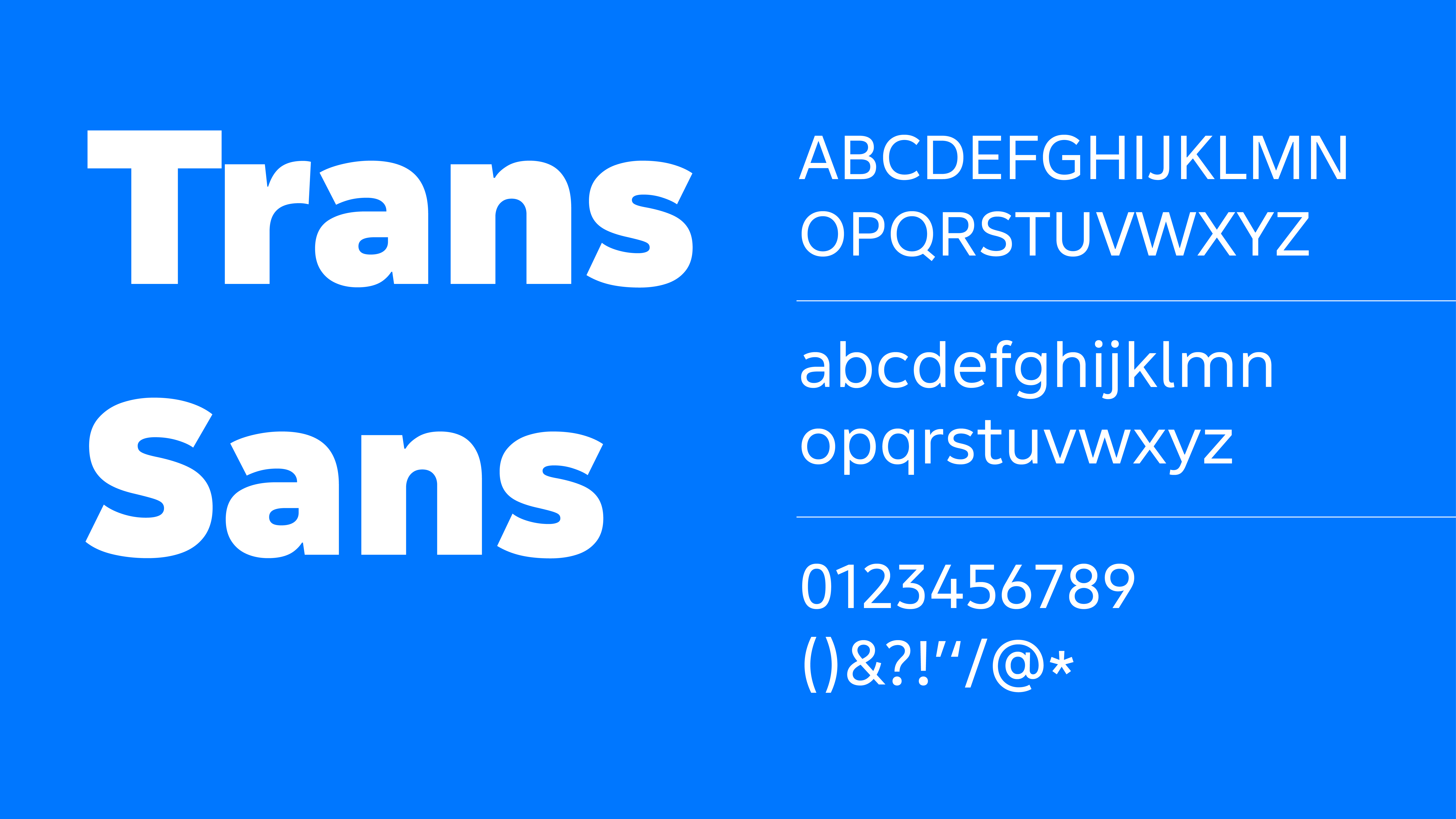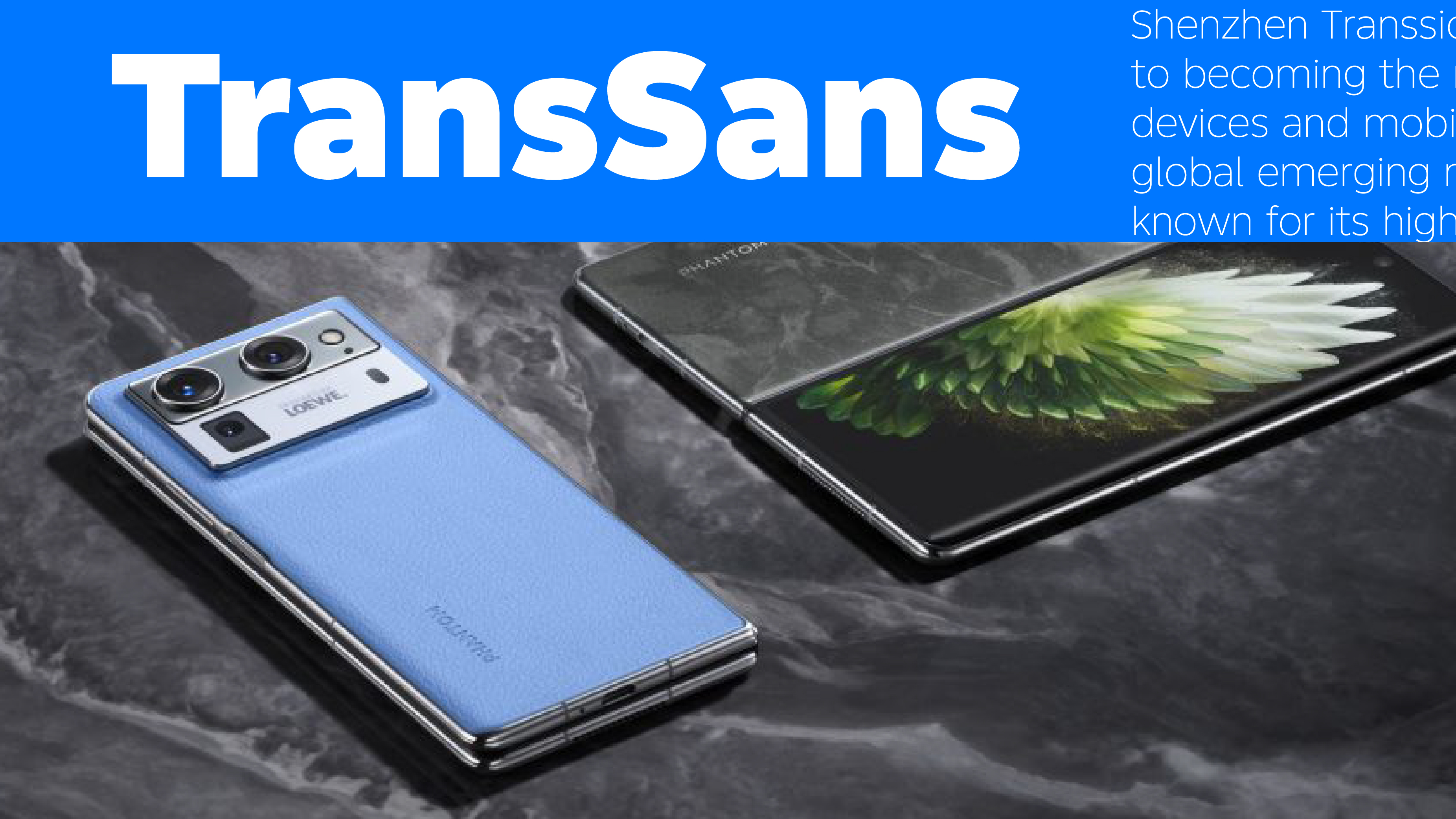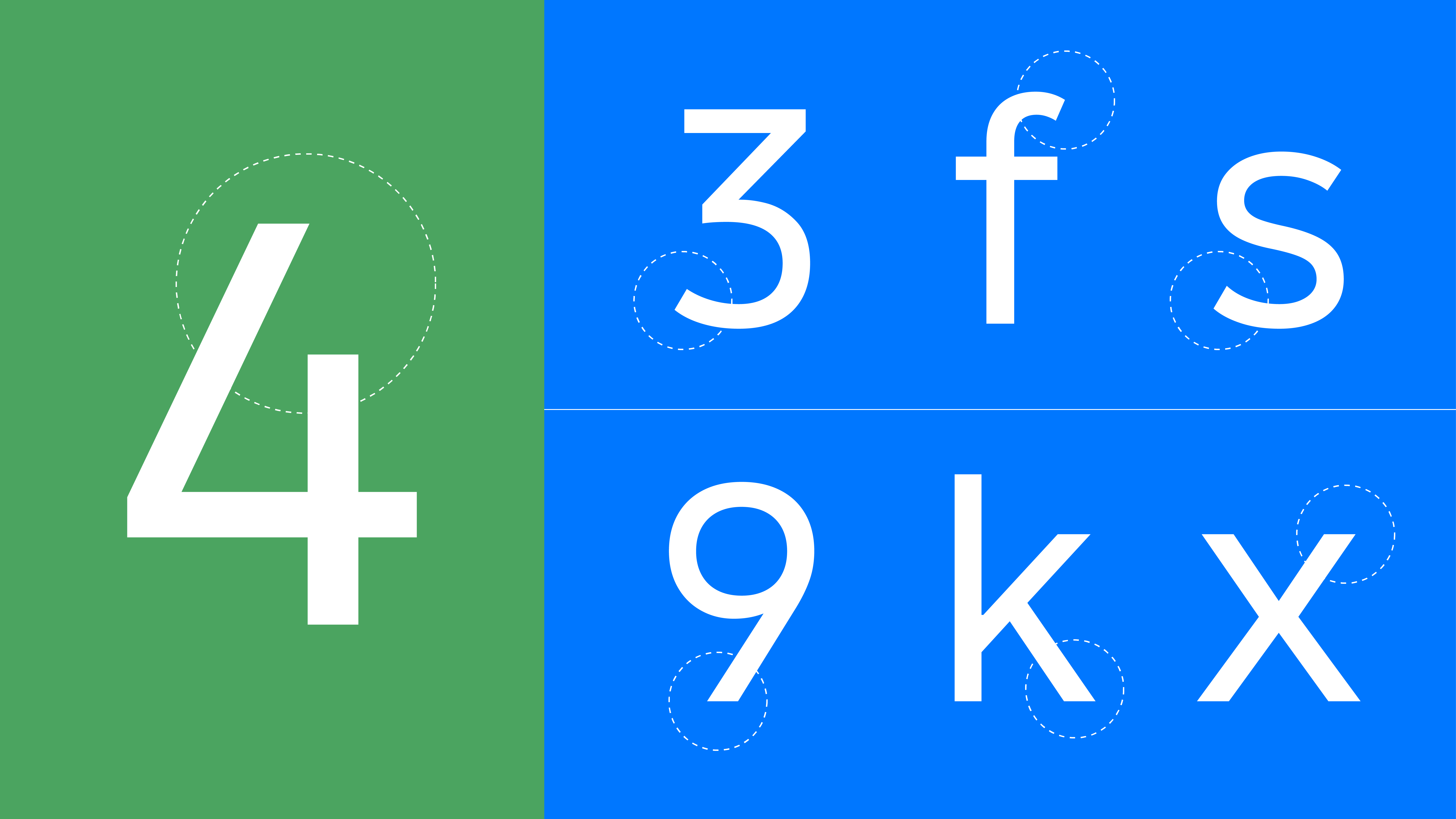
作为新兴市场领先的智能终端设备和移动互联服务提供商,传音旗下拥有 TECNO、itel、Infinix 等知名手机品牌,并自主研发了智能终端操作系统传音 OS(包含 HiOS、itelOs 和 XOS),打造了“手机+移动互联网服务+家电、数码配件”的多元商业生态。
传音始终以新兴市场的消费者为中心,不断洞察和满足新兴市场人民的需求。随着全球业务持续扩展,传音意识到,智能终端产品的系统字体不仅承载着产品的视觉质感,也直接影响着不同语言用户的阅读体验与情感连接。
基于传音全球化发展的需求,蒙纳字库打造的新字体在多语言、多文字体系下为不同使用场景带来更清晰、舒适的阅读体验,稳定适配不同字号和分辨率。
此外,新字体兼具传音旗下手机品牌 TECNO“现代科技”和 lnfinix“年轻、潮酷”的品牌气质,同时融合 itel 的“ 可靠、亲和”,整体风格稳健且不失区分度。
通过字体的系统性升级,传音进一步提升了界面的视觉品质和品牌的统一性,为全球用户带来更为一致、更加温和的交互感受。
设计师
Emilios Theofanous
蒙纳字体创意总监 Emilios Theofanous 出生于塞浦路斯,对高质量的希腊语和多语种文字设计情有独钟。他曾和国际上的字体公司合作,并参与大型字体项目,比如 Google Fonts 和 Adobe 的 Source Serif 希腊文斜体。加入蒙纳后,他参与了多个定制和字体库项目。